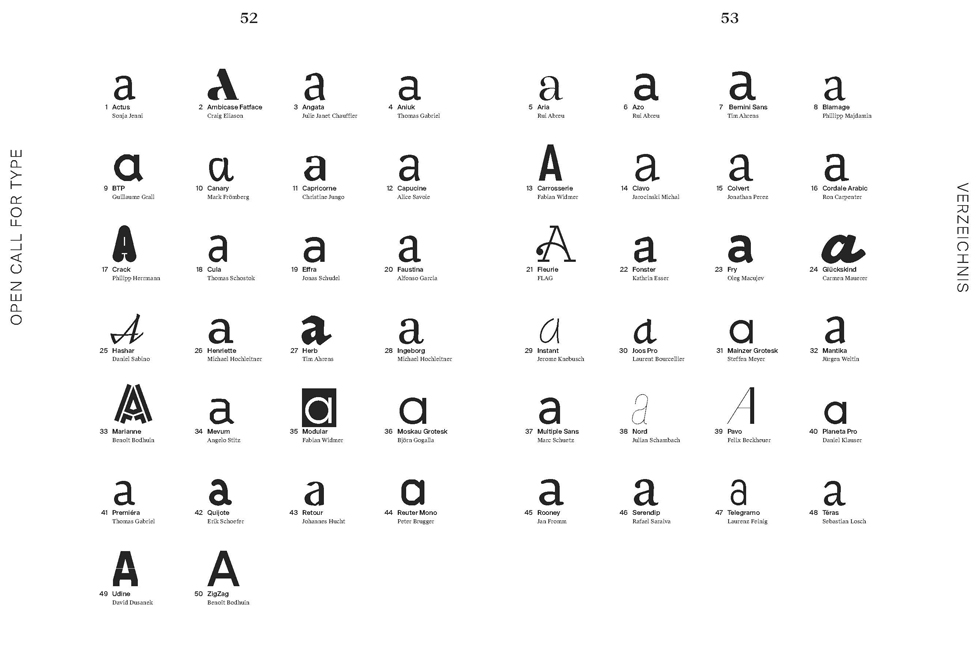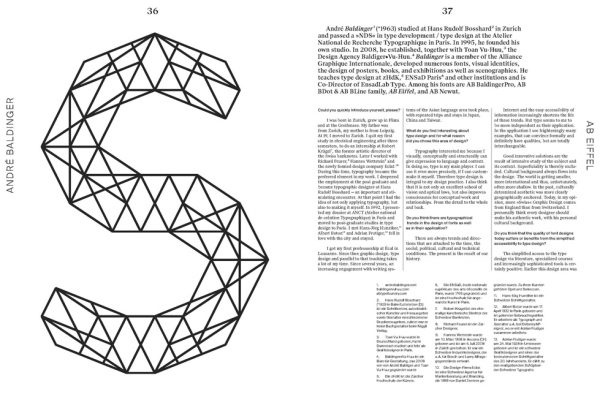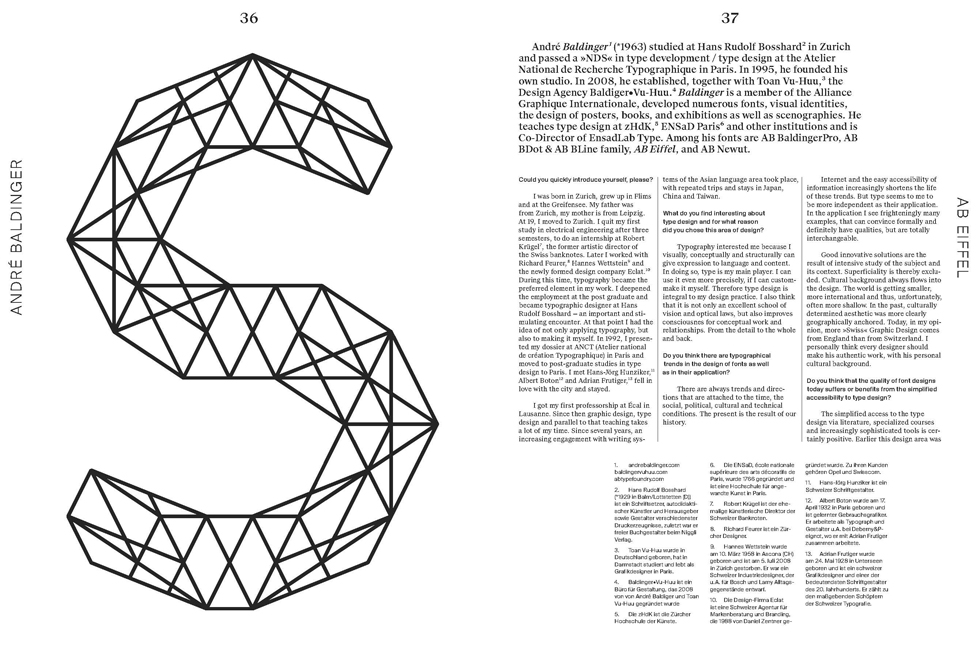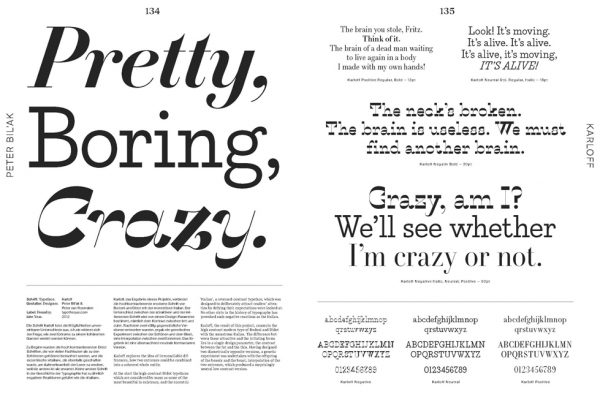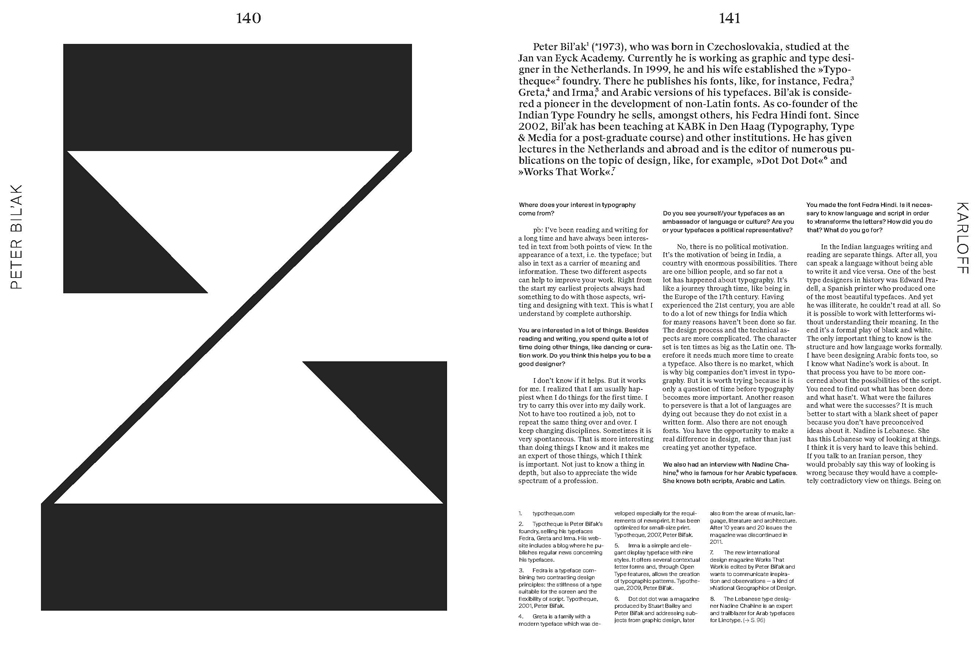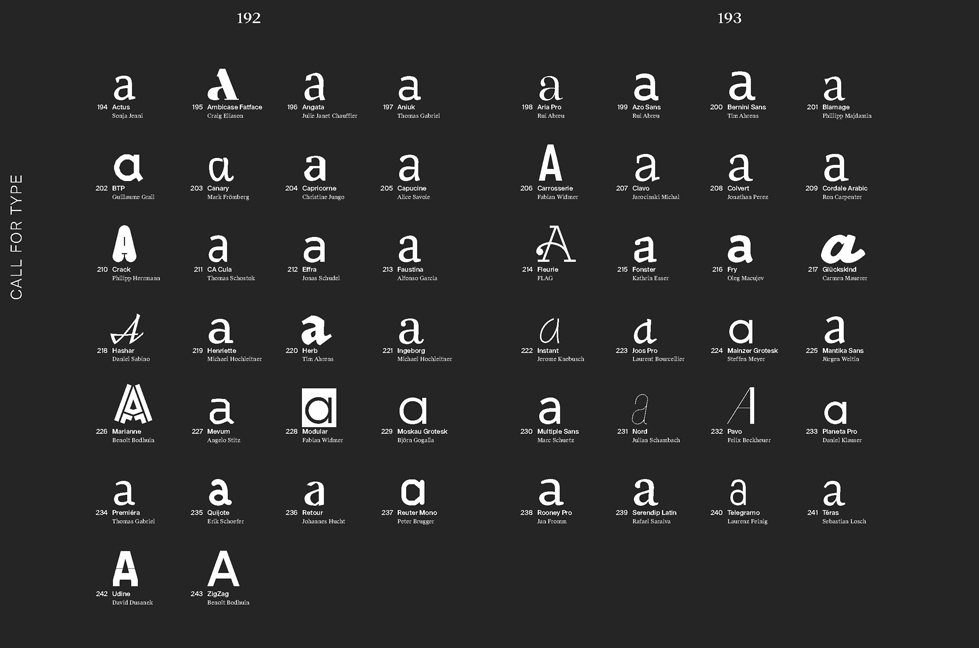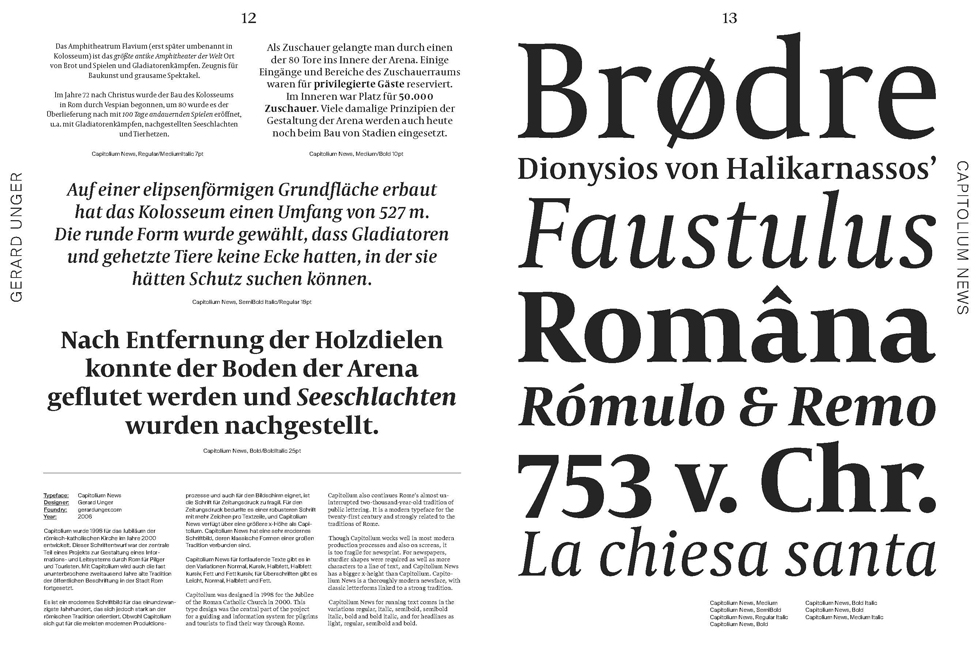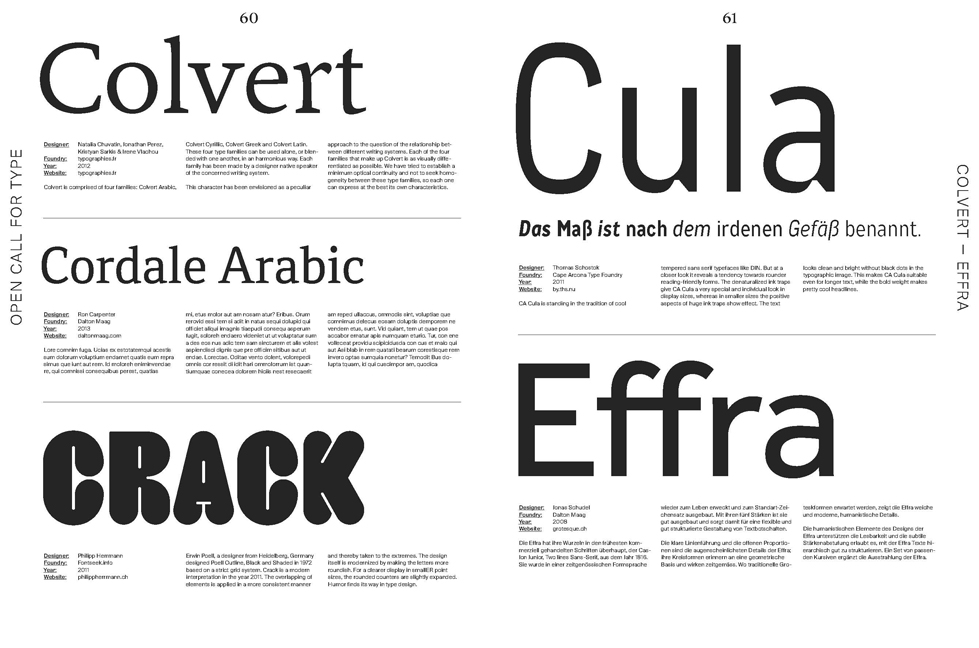
Neue Schriften. New Typefaces.
Positionen und Perspektiven
Wurden in den 1970er-Jahren jährlich noch wenige hundert Schriften veröffentlicht, können wir heute zwischen zehntausenden Fonts wählen. Dass sich aktuelles Type-Design dennoch keinesfalls in Beliebigkeit oder einem modischen Hype erschöpft, verdeutlicht diese Publikation: Aus dem reichen, internationalen Schriftkosmos präsentiert sie experimentelle Schriftentwürfe, die von einer spontanen Idee oder der Konzeption eines selbst gewählten Gestaltungsprojekts ausgehen.
Diese Publikation stellt Positionen des zeitgenössischen Schriftentwurfs in Wort und Bild vor: Wichtige Protagonisten berichten über ihr Denken und Arbeiten und präsentieren ihre zum Teil prämierten Werke. In ihrer Gesamtheit dokumentiert die Publikation so nicht nur die hohe Professionalität, sondern auch den ernsthaften Enthusiasmus, der Schriftgestalterinnen und -gestalter heute antreibt.